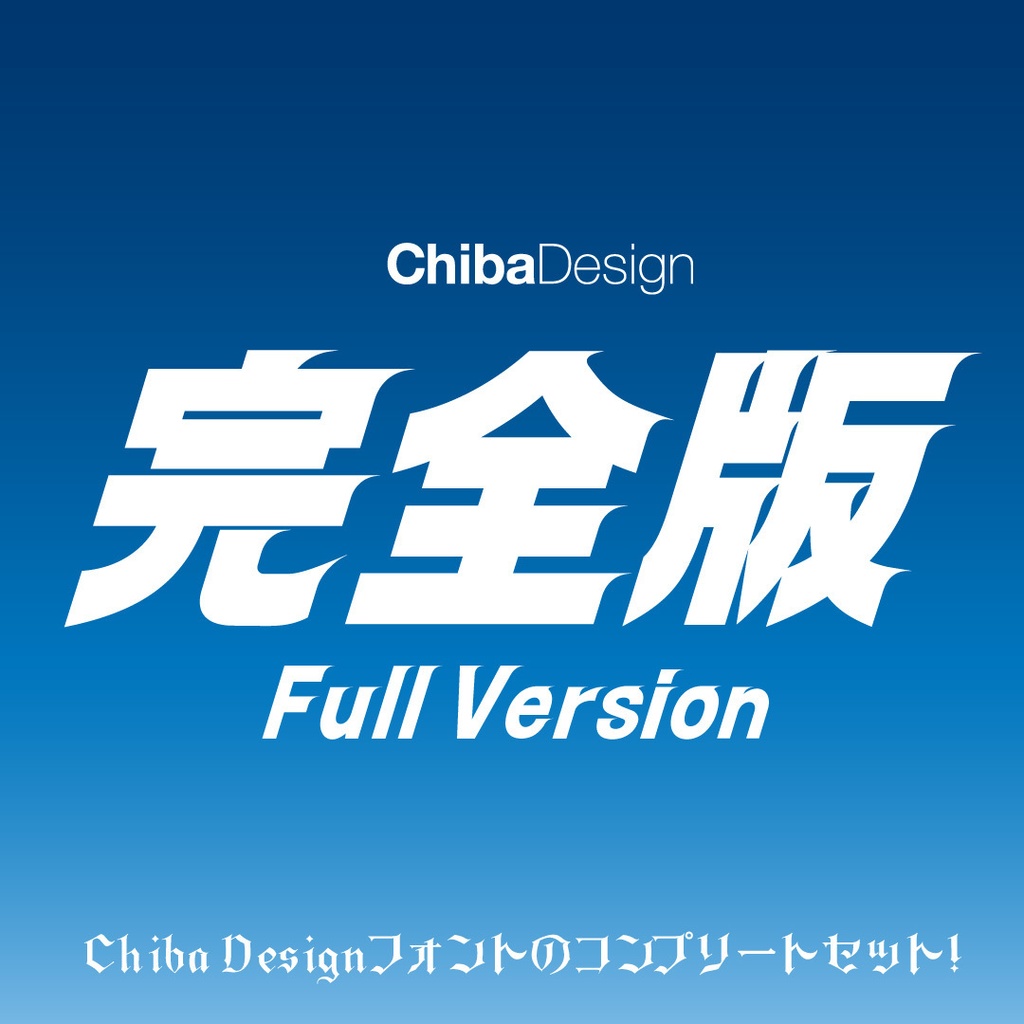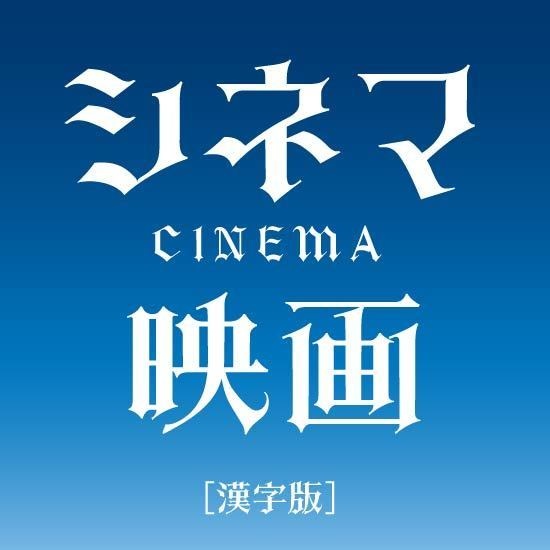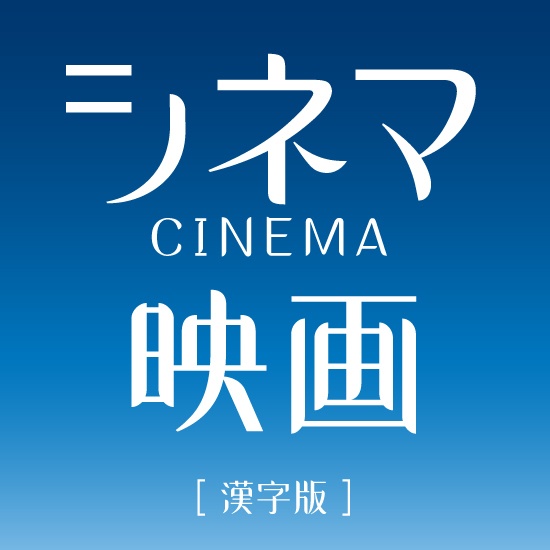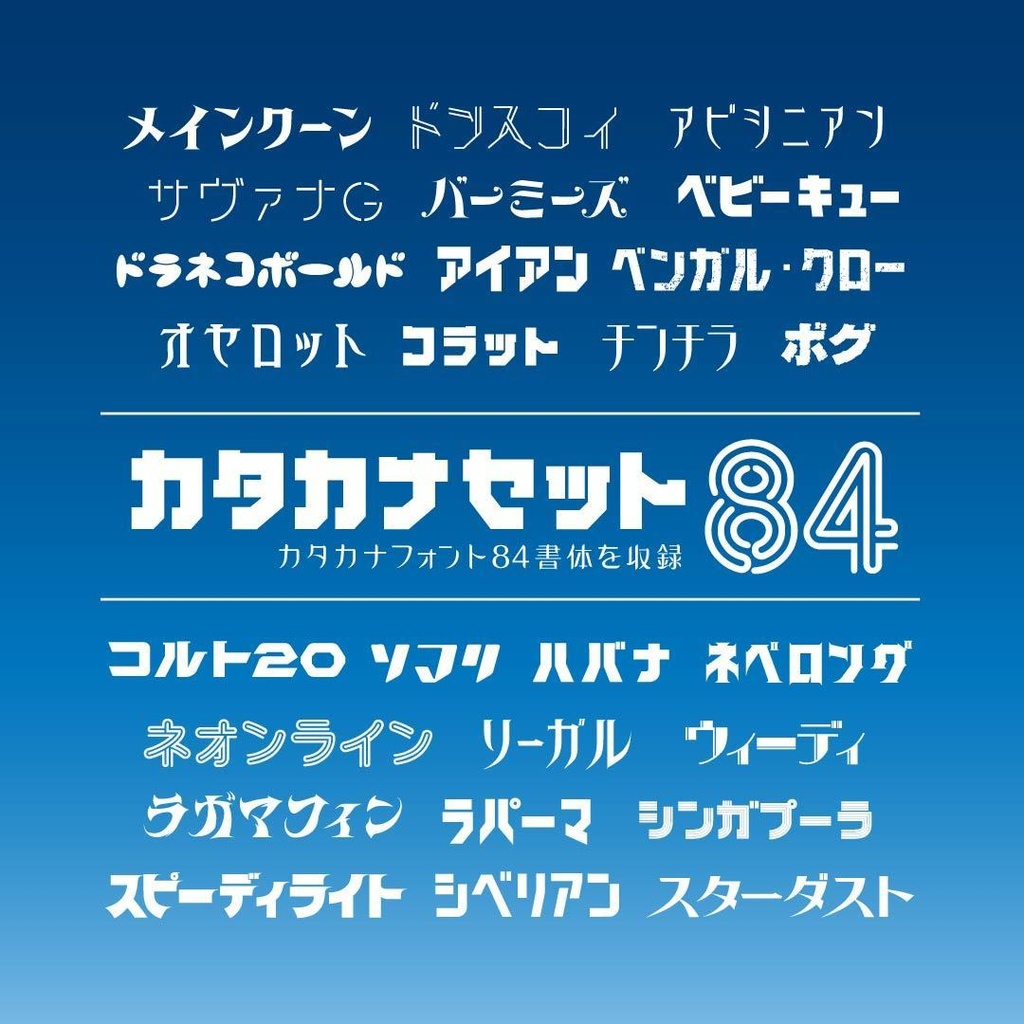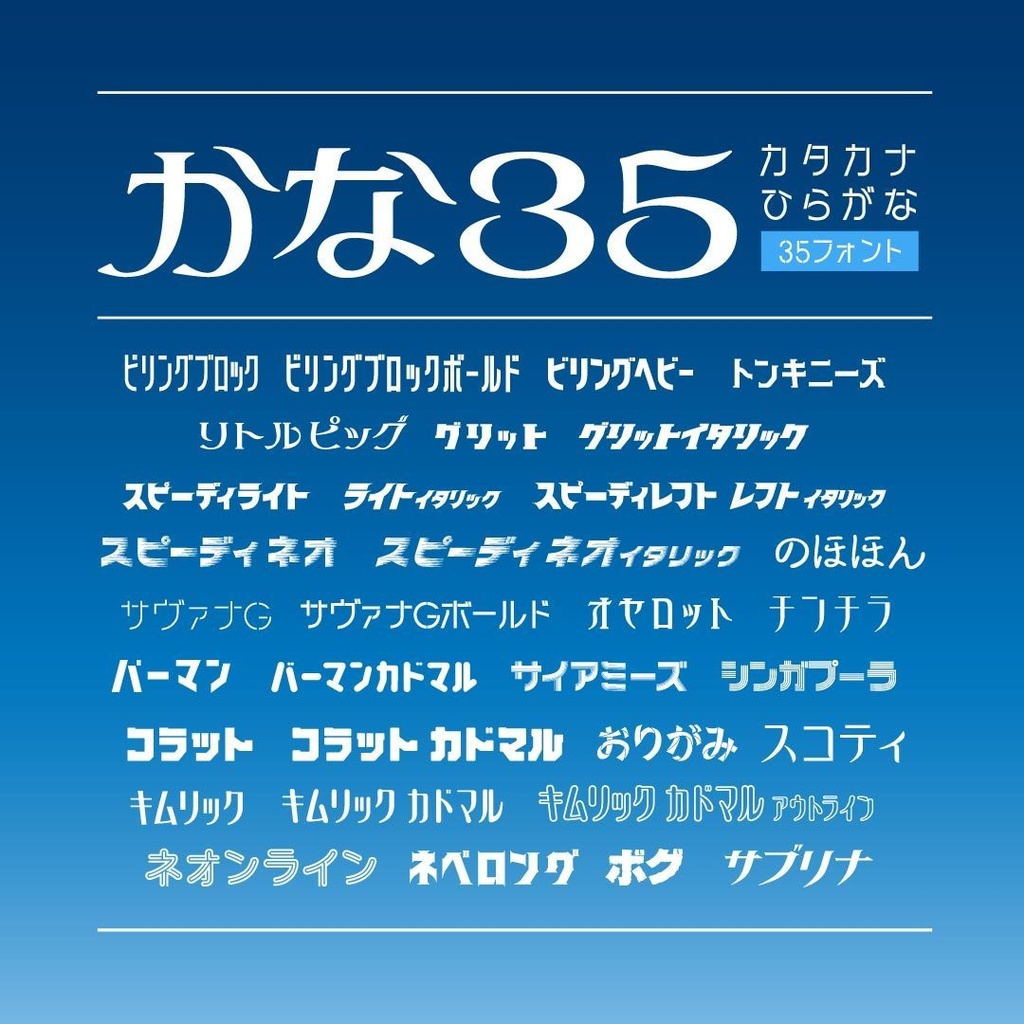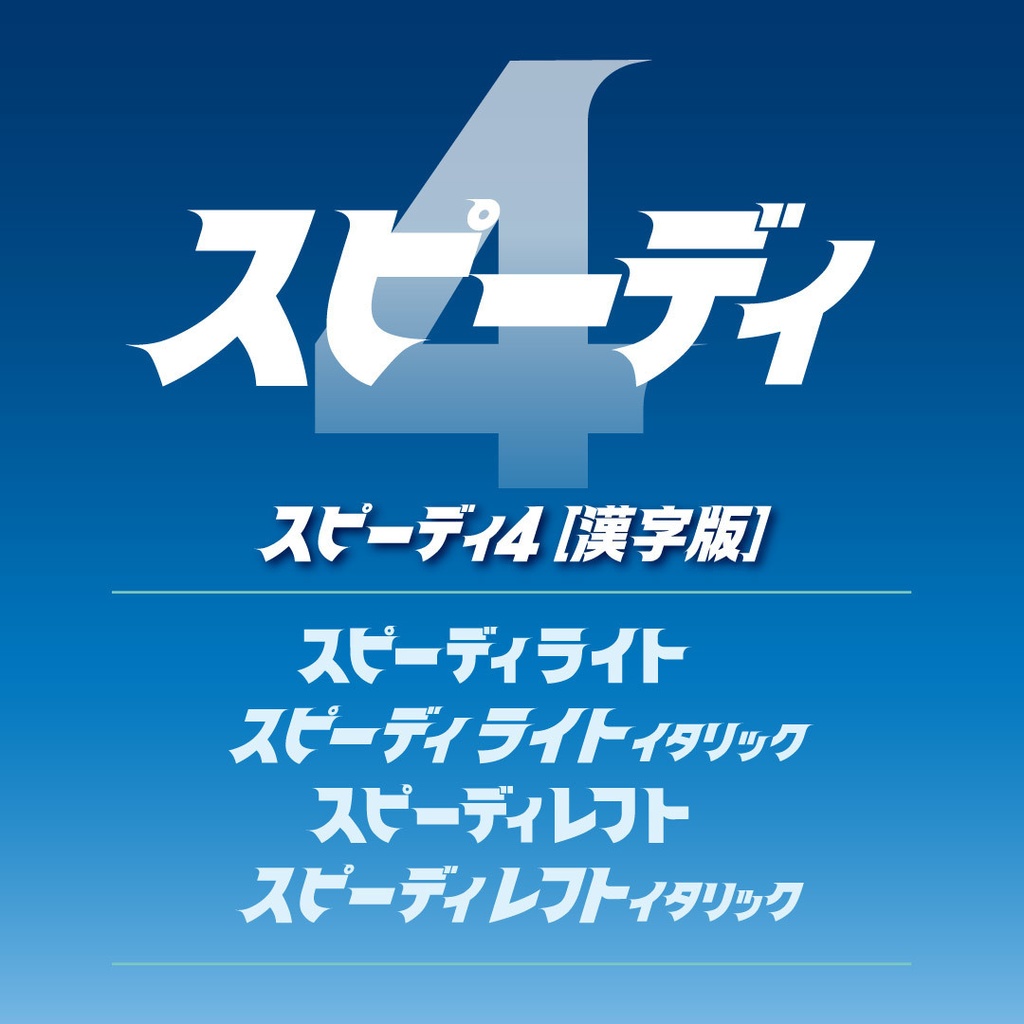
Chiba Designフォント完全版
シネマロゴを手掛けるChiba Designのフォント。
Chiba Designフォント完全版
Chiba Designでは、豊富なフォントを取り揃えています。このコンピレーションは、今まで制作したフォントを全て収録。『カタカナセット』、『かなセット』、『スピーディ4漢字版』、『スコティ』『ブレード』漢字版も収録。ポスター、ディスプレイ、チラシ、Webバナー、広告、ロゴデザイン他、印刷物などにお使いいただけます。 収録フォントセット ◉カタカナセット84 ◉かな35 ◉スピーディ4【漢字版】 ◉スコティ【漢字版】 ◉ブレード【漢字版】 ■Open Type・2バイト。 ■商用利用ok。 ■対応OS:MacOS X(10.x) Windows 7以降。 ●使用許諾について http://www.chiba-design.com/license.html